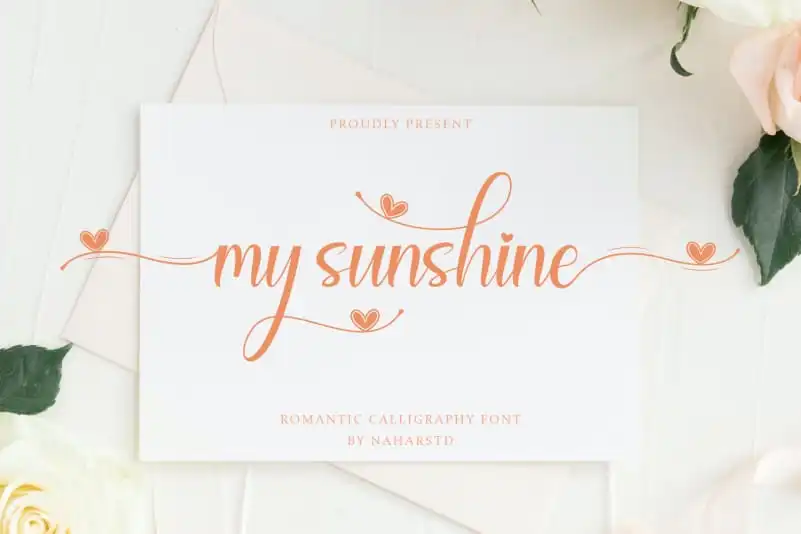
My Sunshine Calligraphy Font – Download Grátis
Descubra a beleza delicada do My Sunshine Calligraphy Font, uma elegante tipografia chinesa desenvolvida para qualquer projeto que você possa imaginar. Com seu toque romântico e versátil, essa fonte se adapta perfeitamente para um vasto leque de aplicativos, incluindo logomarcas, projetos de marca, design de móveis, embalagens de produtos, chinelos, cartões de citação, cartões de convite, capas de livro, selinhos, etiquetas, água-furtuna, presentes especiais e muito mais. Seja para um projeto pessoal ou corporativo, My Sunshine Calligraphy Font é sua fonte perfeita para criar designs únicos que encantam com uma delicada elegância. Engane-se entre as letras do My Sunshine e permita-se ser envolvido por seu ar de sol nascido da manhã.
Designer: Naharstd